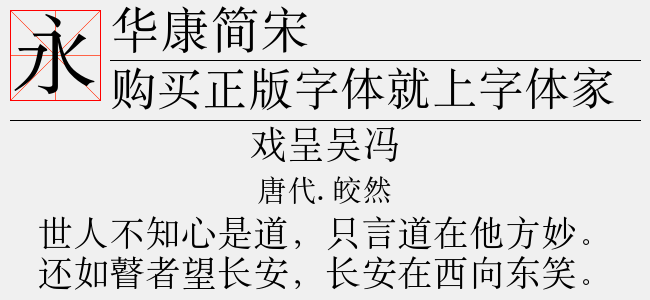
华康简宋(2.70 MTTF中文字体下载)
华康简宋 字体大小2.70 M,包含了6763个汉字以及附加其他英文字体和阿拉伯数字,属于华康字库。华康简宋(TTF)可以免费下载,商业用途请自行购买版权,它的特征就是宋体,印刷,公文,内文,采用安装嵌入的安装方式,支持符号拉丁文日文中文等语言
字体名称:华康简宋